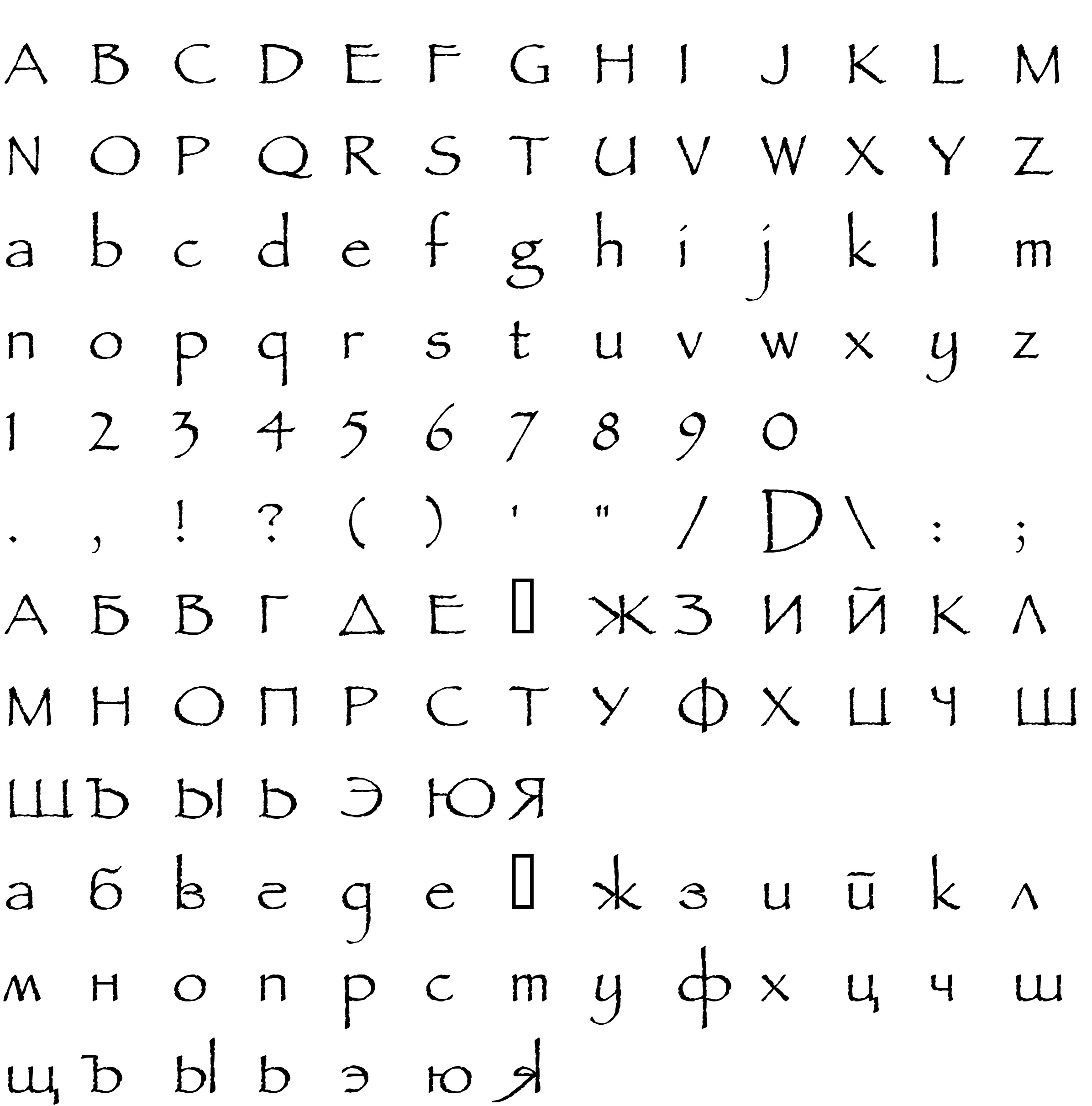
Идеи и советы по применению шрифта Papyrus
Шрифт Papyrus — популярный декоративный выбор для дизайнеров, но требует осторожного применения. В этой статье мы собрали вдохновляющие примеры и полезные рекомендации для его использования.
Используйте шрифт Papyrus для заголовков, чтобы подчеркнуть тему, но избегайте мелкого текста.
Не сочетайте Papyrus с другими декоративными шрифтами, чтобы избежать перегруженности дизайна.
Выбирайте минималистичный фон, чтобы Papyrus выглядел элегантно и не терялся.
Избегайте использования Papyrus в деловых документах и официальных проектах.
Пробуйте регулировать межбуквенное расстояние (кернинг), чтобы улучшить читаемость текста.
Используйте Papyrus в проектах с этнической, исторической или природной тематикой.
Старайтесь использовать не больше двух цветов в тексте с шрифтом Papyrus для гармоничного вида.
Применяйте Papyrus в сочетании с графическими элементами, чтобы усилить визуальный эффект.
Тестируйте разные размеры Papyrus для адаптации под веб или печатный формат.
Избегайте чрезмерного наклона или искажения шрифта Papyrus, чтобы сохранить его уникальный стиль.